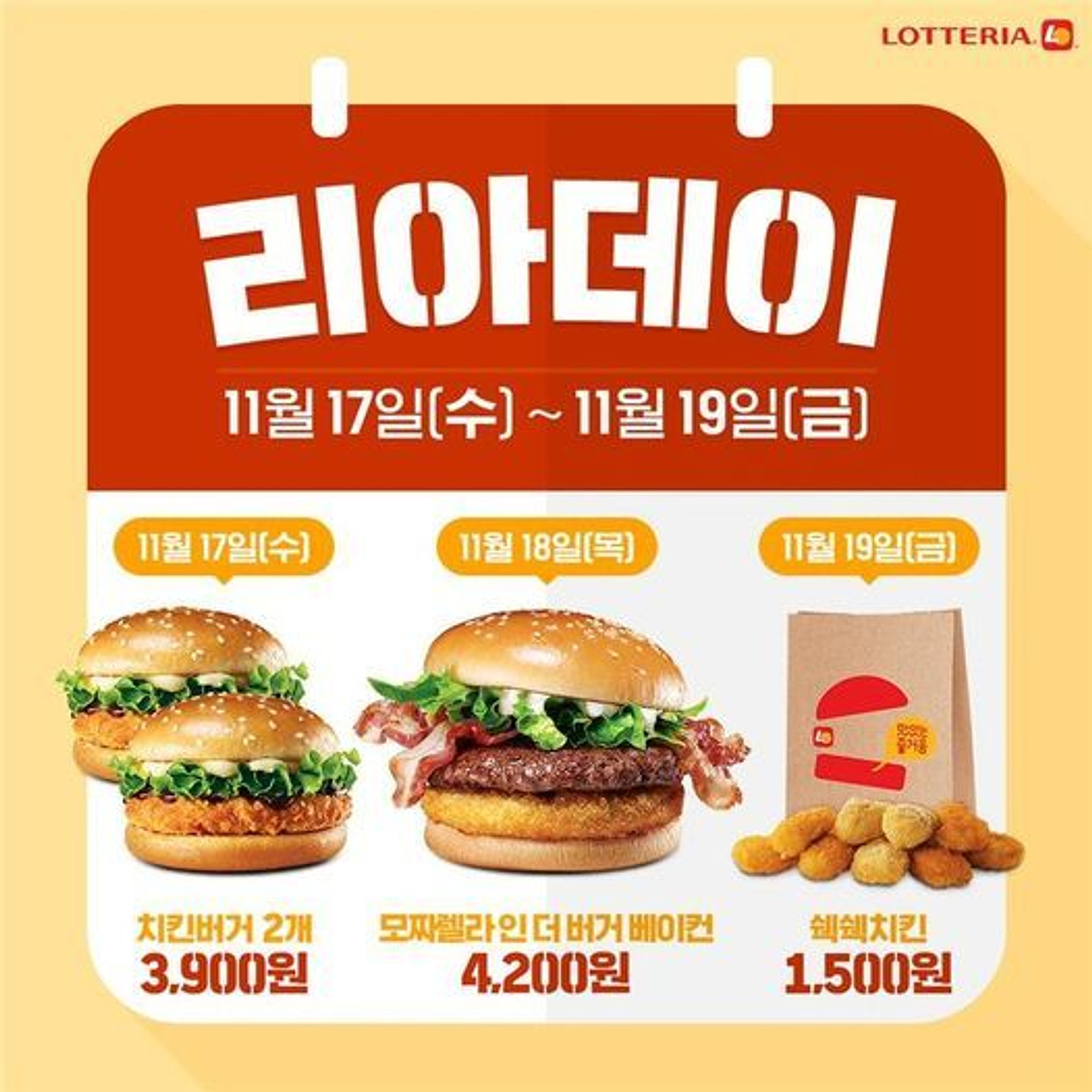
리아데이 폰트궁금합니다
Sandoll 액션스텐실 01 Solid
자소를 컷팅하여 만들어낸 강력한 주목성 산돌 스텐실 제1탄 산돌 '앤션스텐실'은 포스터나 광고 매체에서 강한 주목성을 가질 수 있도록 자소를 절단하여 오는 분절의 이미지를 특징으로 삼아서 만든 서체이다. 판독성을 해치지 않는 선에서 일부 자소에만 분절의 요소를 적용하였고 솔리드한 형태를 기본으로 하여 텍스쳐가 적용된 스타일까지 총 2종의 스타일로 제작되어 다양한 상황에서 사용될 수 있도록 하였습니다.